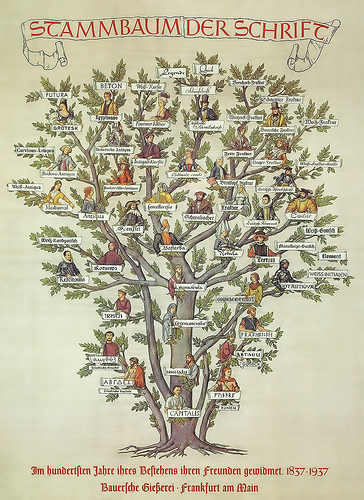
Stammbaum der Schrift von 1962
Wer sich für den Stammbaum der Schrift von 1962 der Braueschen Schriftgießerei interessiert:
Eines der Original-Plakate hängt heute noch, etwas abseits vom Geschehen, in der Druckwerkstatt der Muthesius Kunsthochschule. Und obwohl ein zeitgemäßer Gestalter fast nur zu den Schriften greift, die in diesem Baum noch nicht gewachsen sind, lohnt es sich ein Blick auf die verschiedenen Äste zu werfen — denn viel hat sich bis heute nicht geändert.
Schön, diese Fassung kannte ich noch gar nicht! Den Vorgänger, Fritz Kredels Stammbaum von 1937 (den man beim BfdS bestellen kann), finde ich allerdings schöner.
Braueschen Gießerei → Bauersche Gießerei
Das habe ich jetzt mal getan. Zudem wäre ich an einem hochaufgelösten Scan des Original-Farbholzschnitts interessiert. Vielleicht kann mir da jemand weiterhelfen? – Hm – ich werde einmal das Gutenbergmuseum und das Museum Offenbach befragen.
Schön, diese Fassung kannte ich noch gar nicht! Den Vorgänger, Fritz Kredels Stammbaum von 1937 (den man beim BfdS bestellen kann), finde ich allerdings schöner.